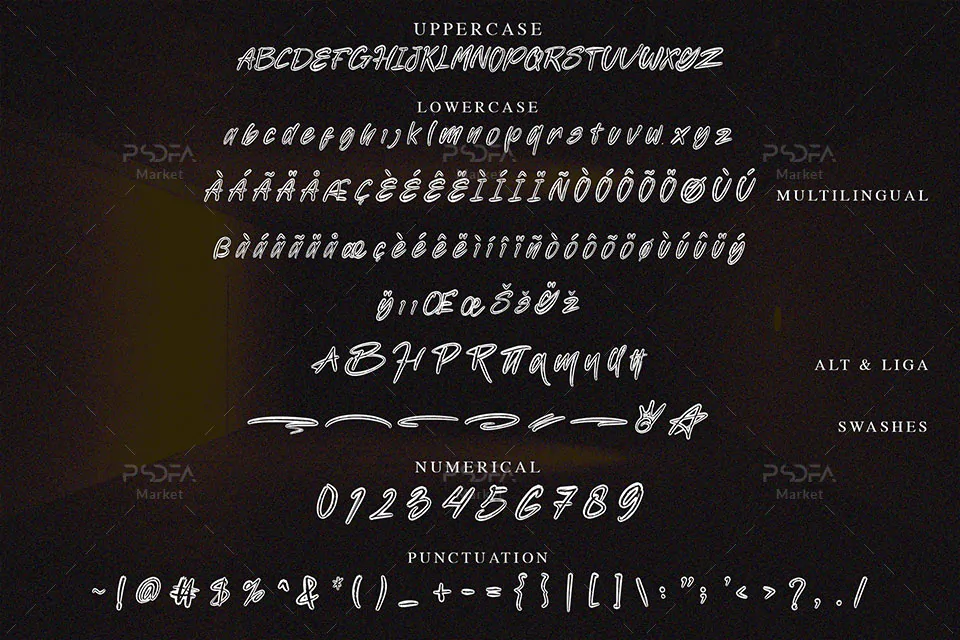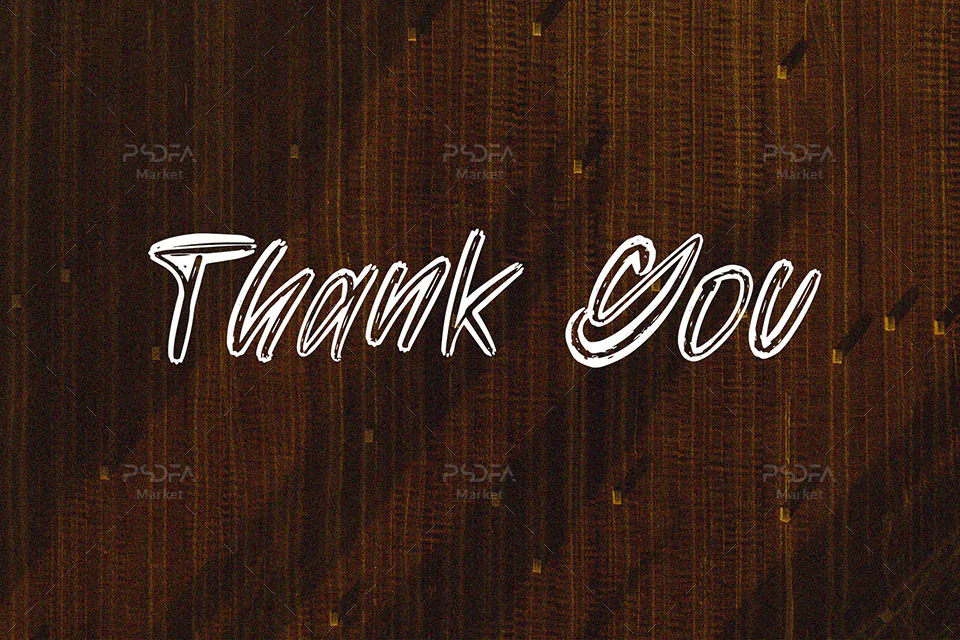
فونت نمایشی و قلمویی Black Gatte یک قلم دستنویس فوق العاده زیبای انگلیسی است که مناسب جهت استفاده در طرح و پروژههای گرافیکی مختلف به خصوص طراحی انواع پوستر میباشد. این فونت زیبا در قالب فایل OTF, TTF در فایل محصول قرار دارد که با نصب یکی از این 2 فرمت در پوشه فونتهای سیستم میتوانید از این فونت انگلیسی در تمام نرم افزارهای گرافیکی و تایپ متون همچون فتوشاپ، افتر افکت، پریمیر، ورد، پاورپوینت و … استفاده کنید.
فونت دستنویس و قلمویی Black Gatte در وزن معمولی (Regular) طراحی شده است که میتوانید از آن در طراحی انواع پوستر، بسته بندی محصولات، لوازم التحریر، بگهای خرید و هدیه، ظروف یکبار مصرف، تقویم، بنر، بروشور، تراکت و دیگر طرحهای گرافیکی استفاده کنید.
- نام فونت: Black Gatte
- وزن: Regular